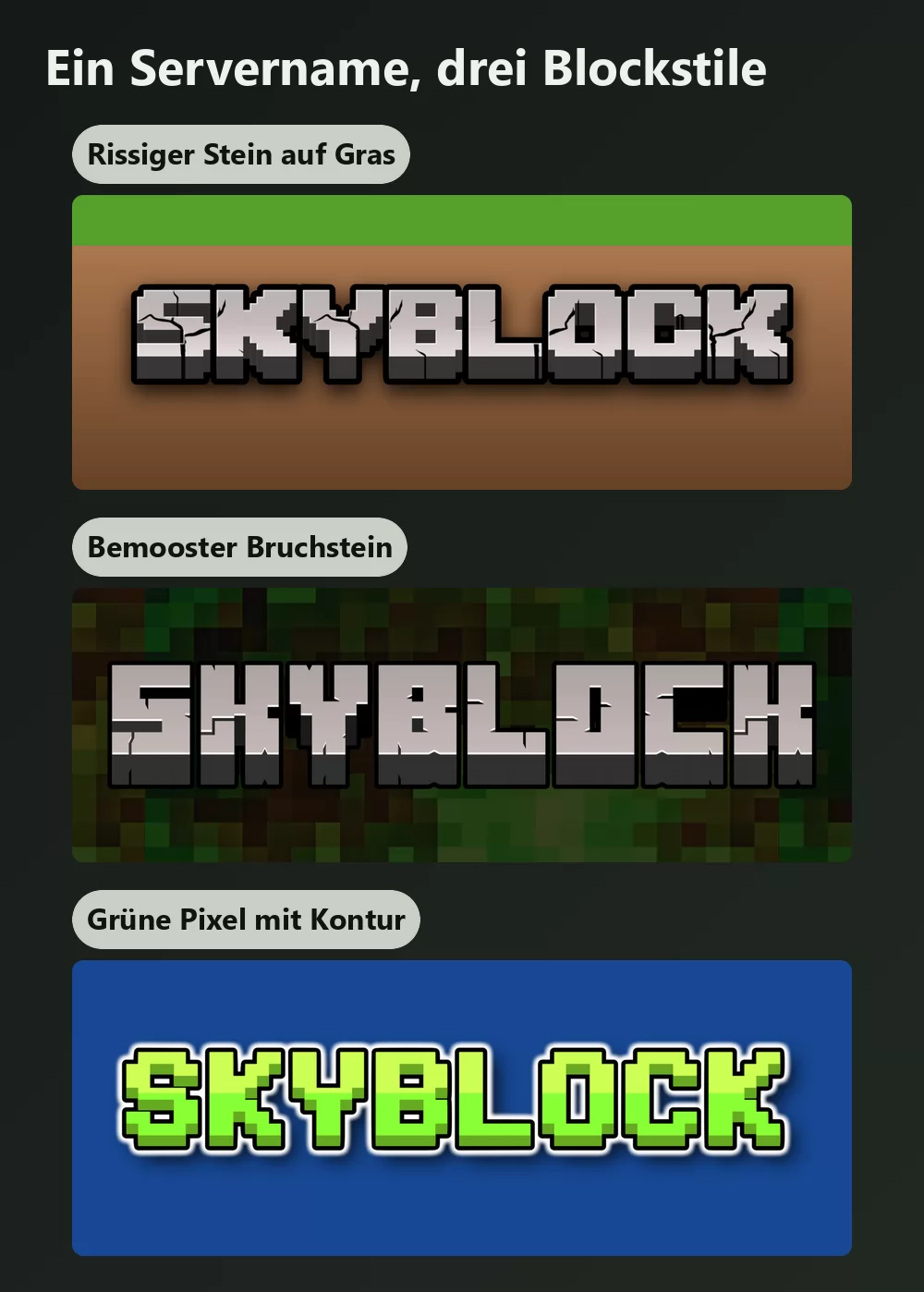
Geben Sie «Minecraft Schriftart» in eine Suchmaschine ein, und Sie bekommen zwei Gruppen von Treffern, die einander widersprechen. Die eine bietet eine flache Pixelschrift. Die andere bietet dicke Steinbuchstaben mit Rissen darin. Beide nennen sich die Minecraft-Schrift.
Beide haben recht, denn Minecraft verwendet zwei völlig verschiedene Schriften, und das Spiel liefert nur eine davon mit. Fast jeder, der danach sucht, hat die zweite vor Augen.
Die kurze Antwort: es sind zwei Schriften, nicht eine
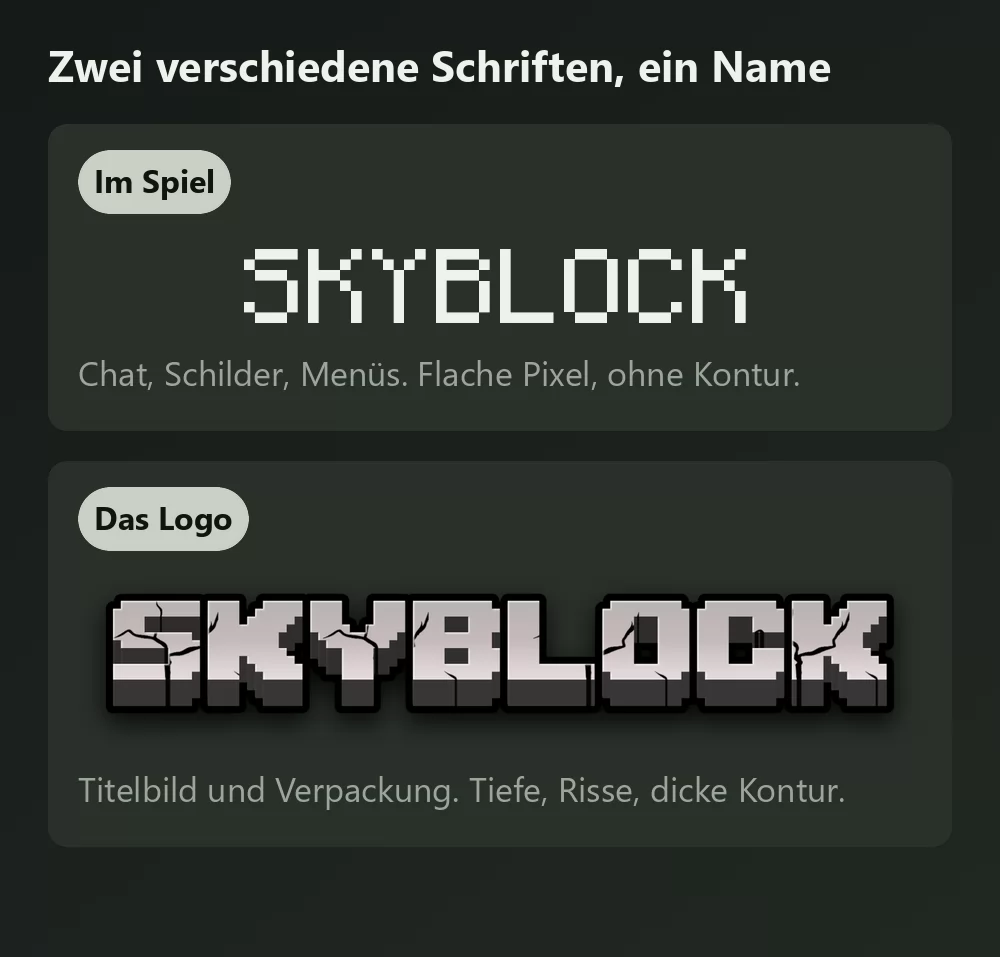
Mojangles ist die, auf der das Spiel läuft. Es ist die kleine Pixelschrift für Chat, Gegenstandsnamen, Schilder, Menüs und jede Anzeigetafel, auf die Sie je die Augen zusammengekniffen haben. Flach, ohne Schattierung, ohne Kontur.
Die Logoschrift ist das dicke, in Stein gehauene Lettering vom Titelbild und von der Verpackung. Sie hat Tiefe, eine schwere dunkle Kontur und Risse quer durch die Buchstaben. Im Spiel existiert sie überhaupt nicht als Schriftart: sie ist eine Illustration.
Wenn Sie ein Server-Banner, ein YouTube-Vorschaubild, ein SMP-Logo oder einen Discord-Header bauen, wollen Sie die zweite. Wenn Sie eine Chatnachricht oder ein Schild nachstellen, die erste.
Woher Mojangles wirklich stammt
Dieser Teil ist wirklich gute Randnotiz, und die meisten Seiten geben ihn falsch wieder.
Mojangles ist älter als Minecraft. Markus Persson zeichnete sie 2001 für ein früheres eigenes Spiel namens Legend of the Chambered, acht Jahre bevor es Minecraft gab, und stützte sich dabei auf die 8 x 8 Pixel große Schrift, die in der IBM-EGA-Grafikkarte von 1984 eingebaut war. Die Schrift, die Sie mit dem meistverkauften Spiel aller Zeiten verbinden, begann ihr Leben als Hardware-Zeichensatz früher PC-Grafikkarten.
Eine Korrektur an dieser Stelle, weil überall das Gegenteil steht: Mojangles ist nicht dicktengleich. Ihre Glyphen sind auf einem 8-Pixel-Raster gezeichnet, aber die Breiten reichen von 1 bis 8 Pixeln, weshalb ein großes M weit mehr Platz braucht als ein kleines i. Mehrere vielgelesene Ratgeber behaupten das Gegenteil. Starten Sie irgendeine Minecraft-Welt und schauen Sie auf ein Schild, die Prüfung dauert zwei Sekunden.
Jede herunterladbare «Minecraft-Schrift» ist also die Nachbildung von irgendjemandem. Das ist völlig in Ordnung, und einige sind ausgezeichnet. Es heißt nur, dass Sie die Lizenz des Nachbildners einhalten müssen, nicht die von Mojang.
Die Schriften, die Sie wirklich laden können, und was jede erlaubt
Monocraft, die mit der sauberen Lizenz
Wenn Sie den Look aus dem Spiel wollen und ruhig schlafen möchten, ist das die Antwort. Monocraft von Idrees Hassan ist eine dicktengleiche Schrift, die sich an der Oberflächenschrift von Minecraft orientiert und unter der SIL Open Font License 1.1 steht. Das heißt: frei, kommerzielle Arbeiten eingeschlossen, mit Namensnennung.
Sie ist außerdem die vollständigste der Gruppe: über 1.500 Glyphen für akzentuiertes Latein, Kyrillisch und Griechisch, dazu das Standard-Galaktische Alphabet vom Zaubertisch. Ausgeliefert wird sie als .ttf und .ttc, und der Autor stellt ausdrücklich klar, dass es ein Fanprojekt ohne jedes Mojang-Material ist.
Zwei Dinge sollten Sie wissen. Sie ist bewusst dicktengleich, anders als Mojangles, weil sie als Programmierschrift entstand: lange Wörter wirken daher etwas breiter als im Spiel. Und sie hat keine chinesischen, japanischen oder koreanischen Glyphen, was zählt, falls Sie CJK-Text damit setzen wollten.
Die kostenlosen Pixel-Nachbildungen
Die meistgeladene heißt schlicht «Minecraft», von Craftron Gaming, und liegt bei knapp fünf Millionen Downloads auf DaFont. Es ist eine 6 KB große TrueType-Datei, die den flachen Look aus dem Spiel nachbildet, und DaFont führt sie als 100 % kostenlos.
Darf ich die Minecraft-Schrift auf Waren nutzen, die ich verkaufe? Schriftlizenz und Marke sind zwei getrennte Fragen. Selbst mit einer freizügig lizenzierten Schrift gehört der Name «Minecraft» Mojang, prüfen Sie also deren Richtlinien zur kommerziellen Nutzung, bevor Sie etwas verkaufen.